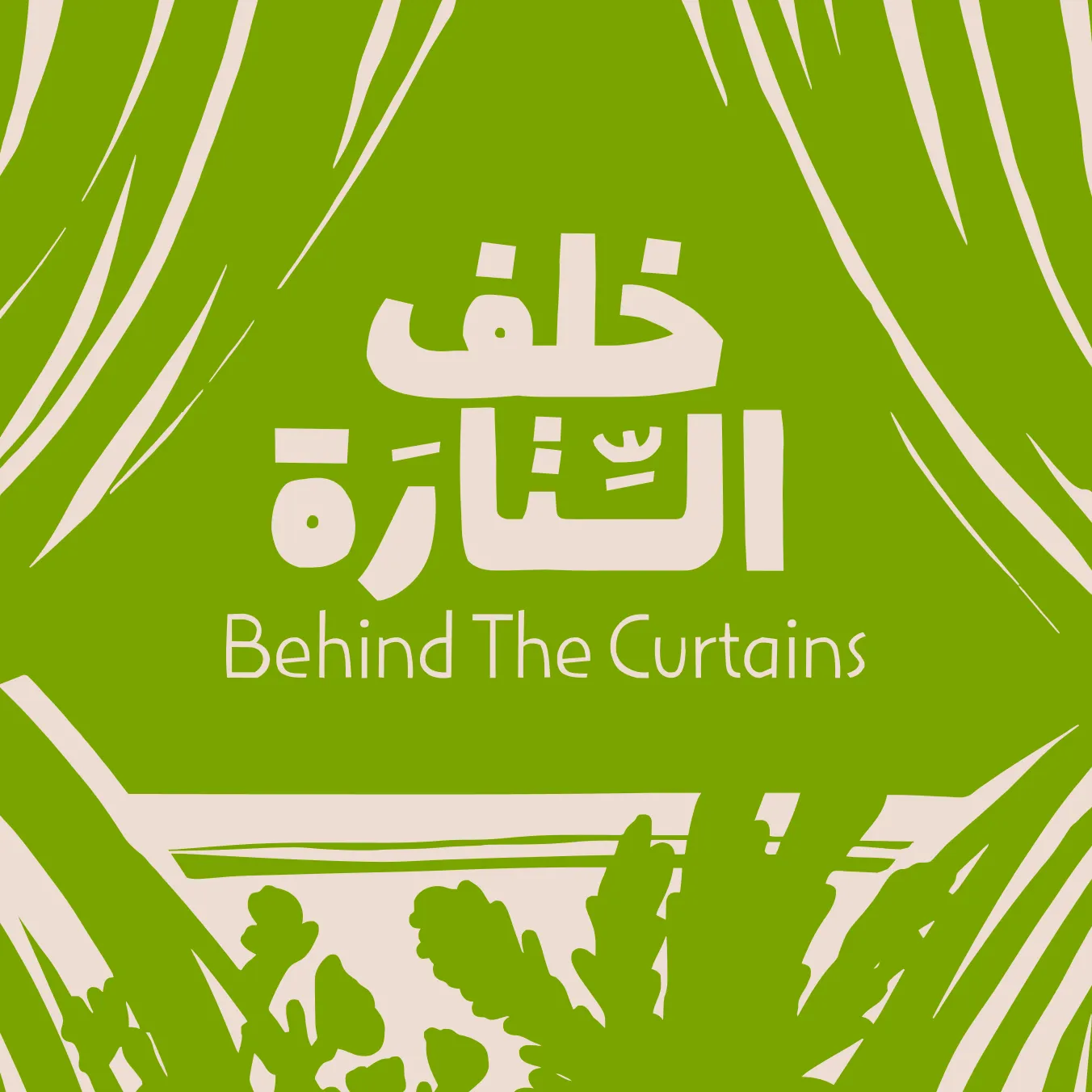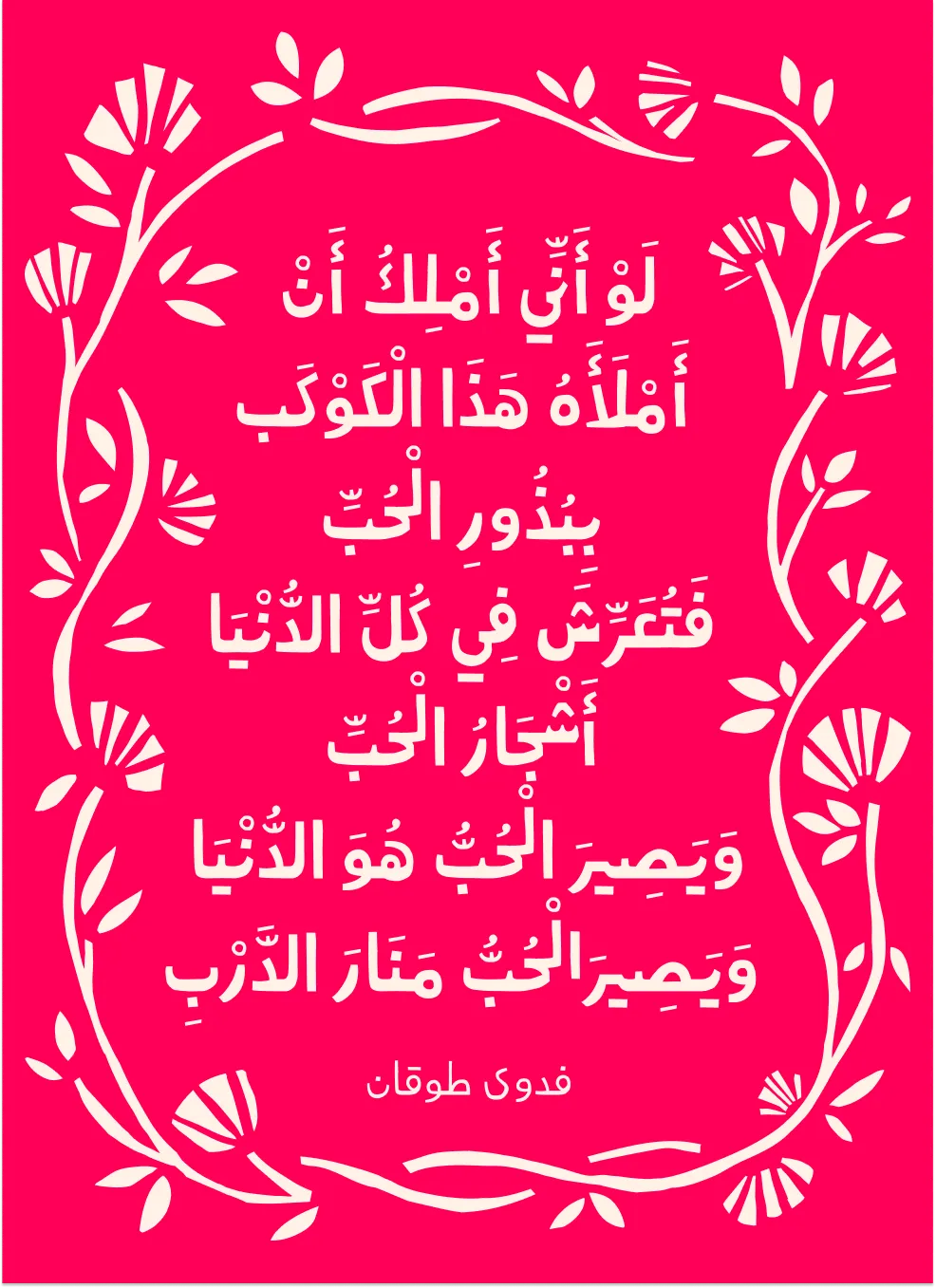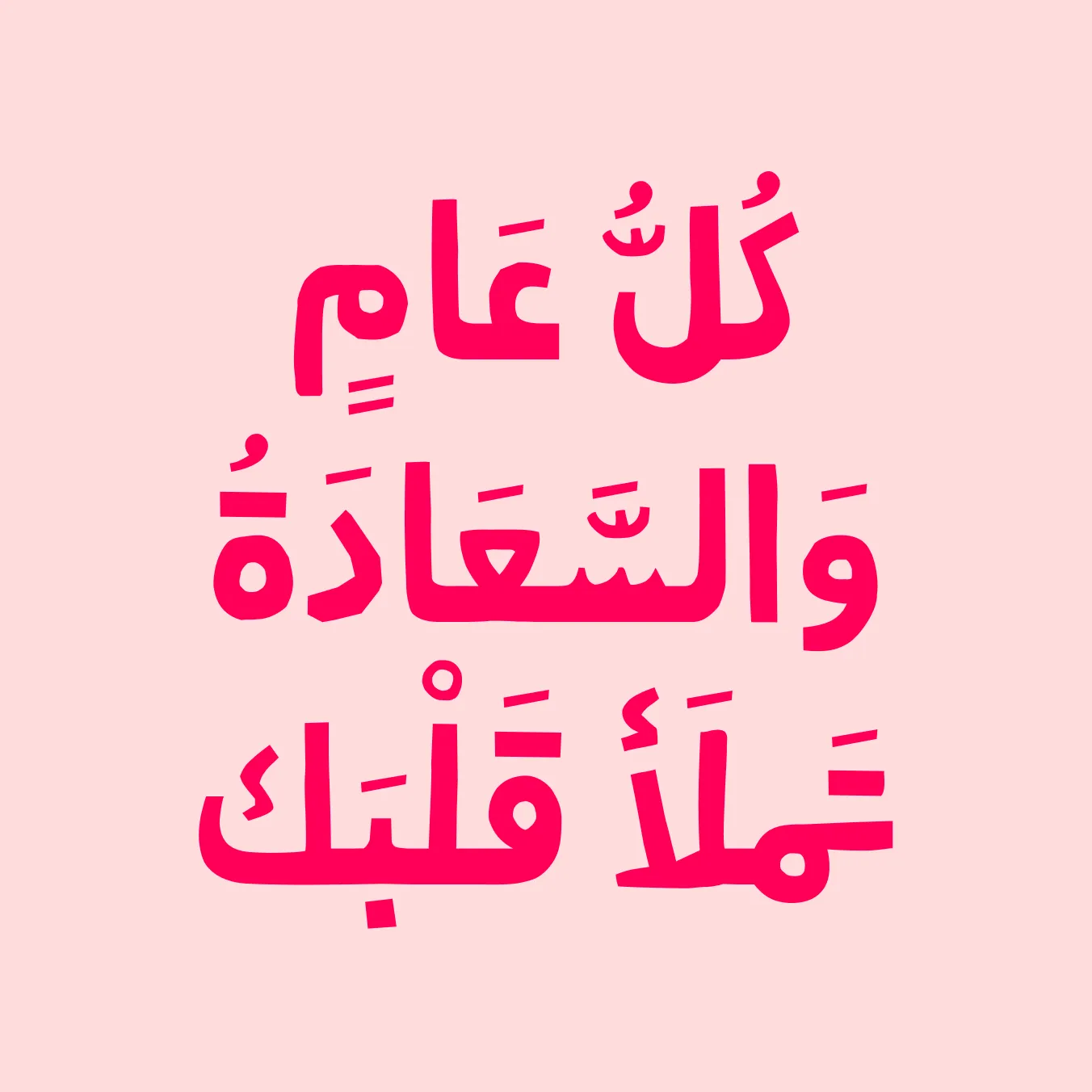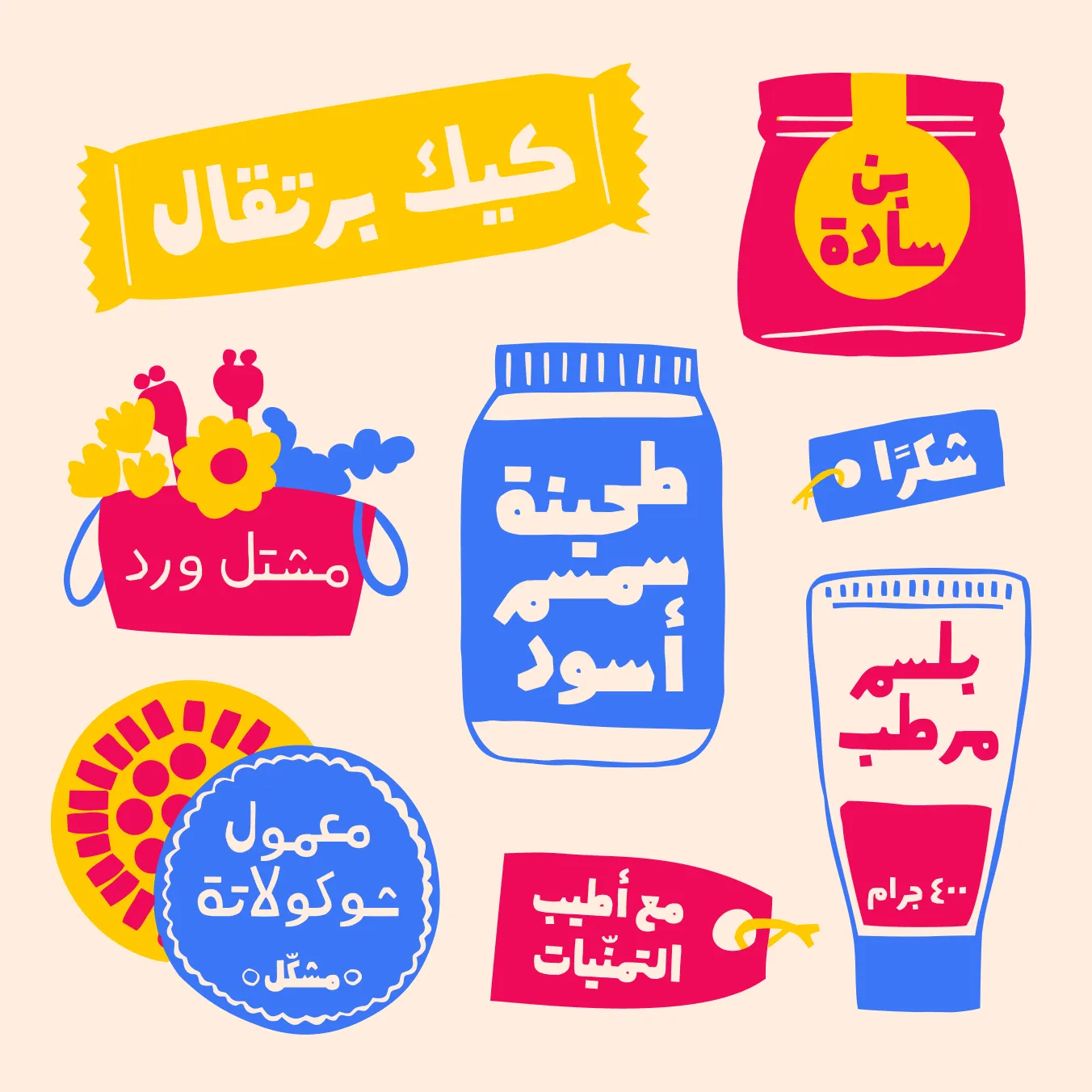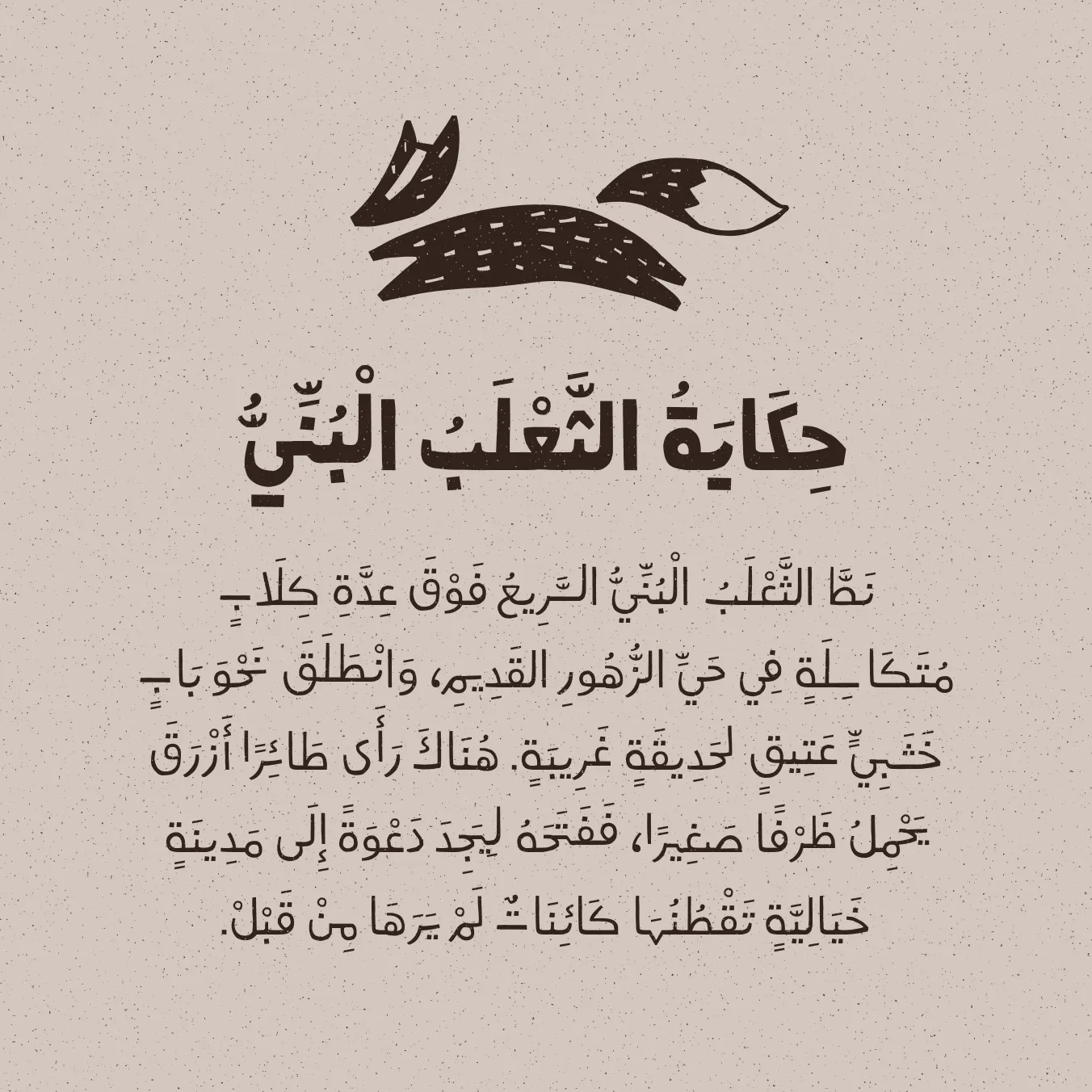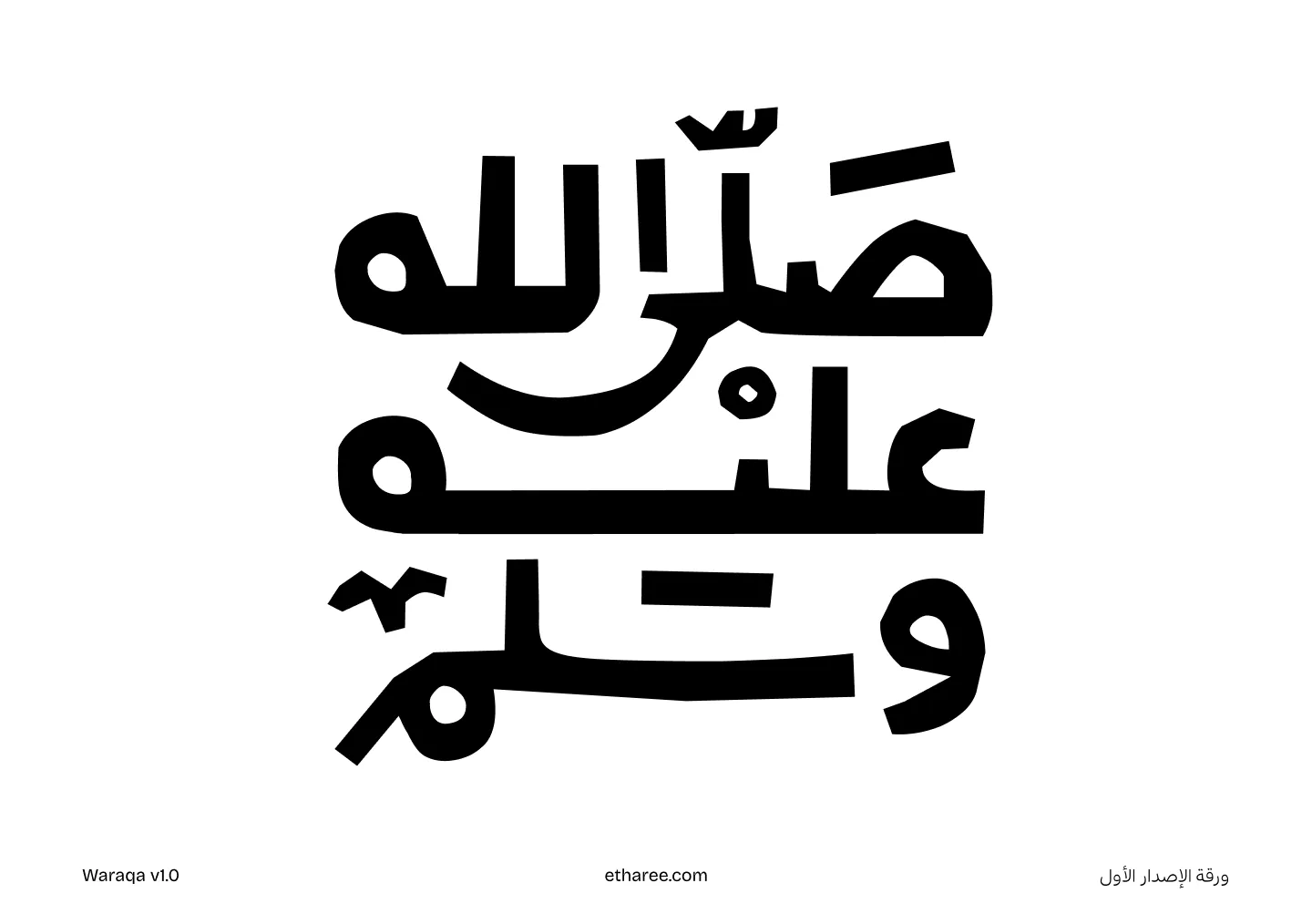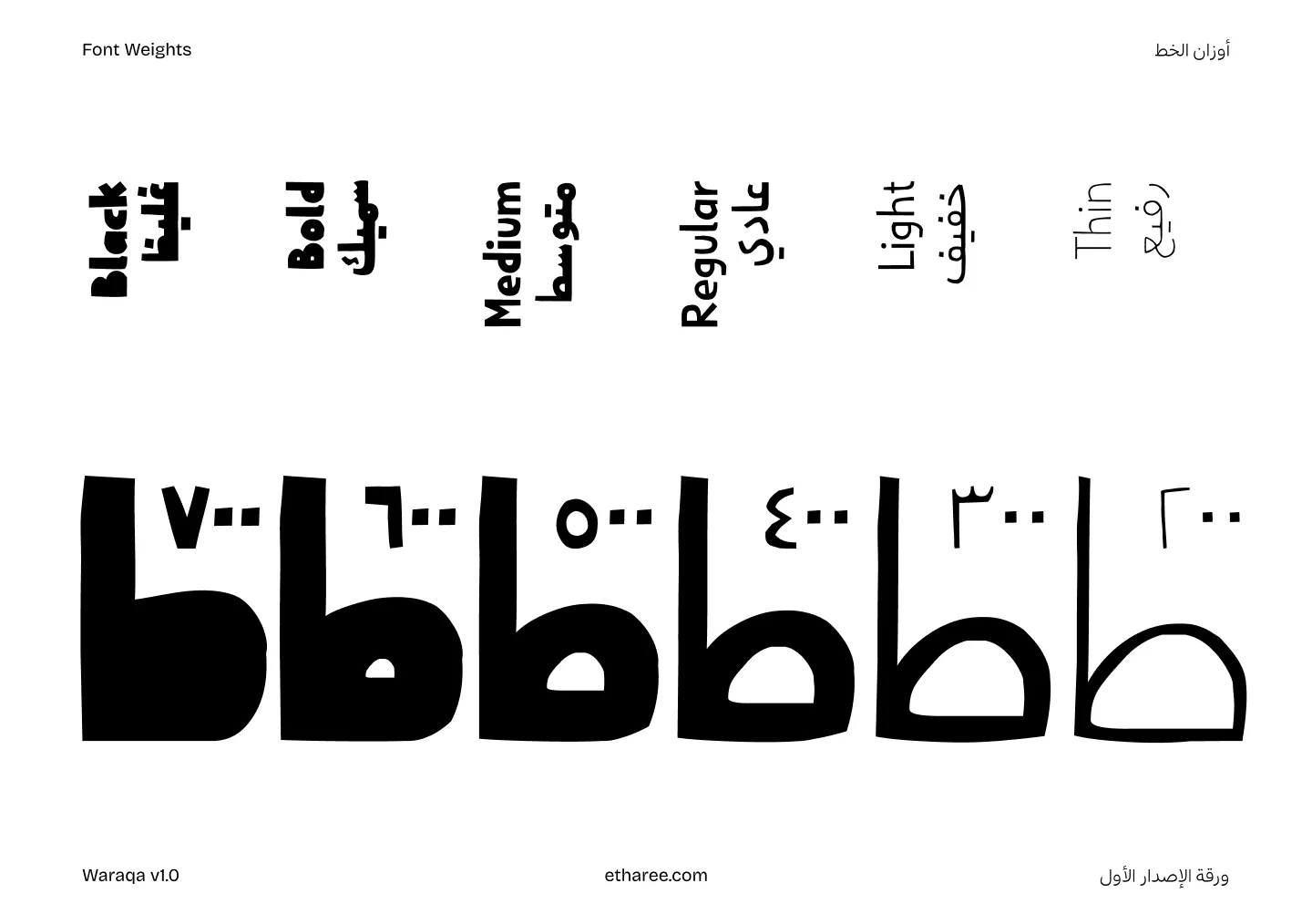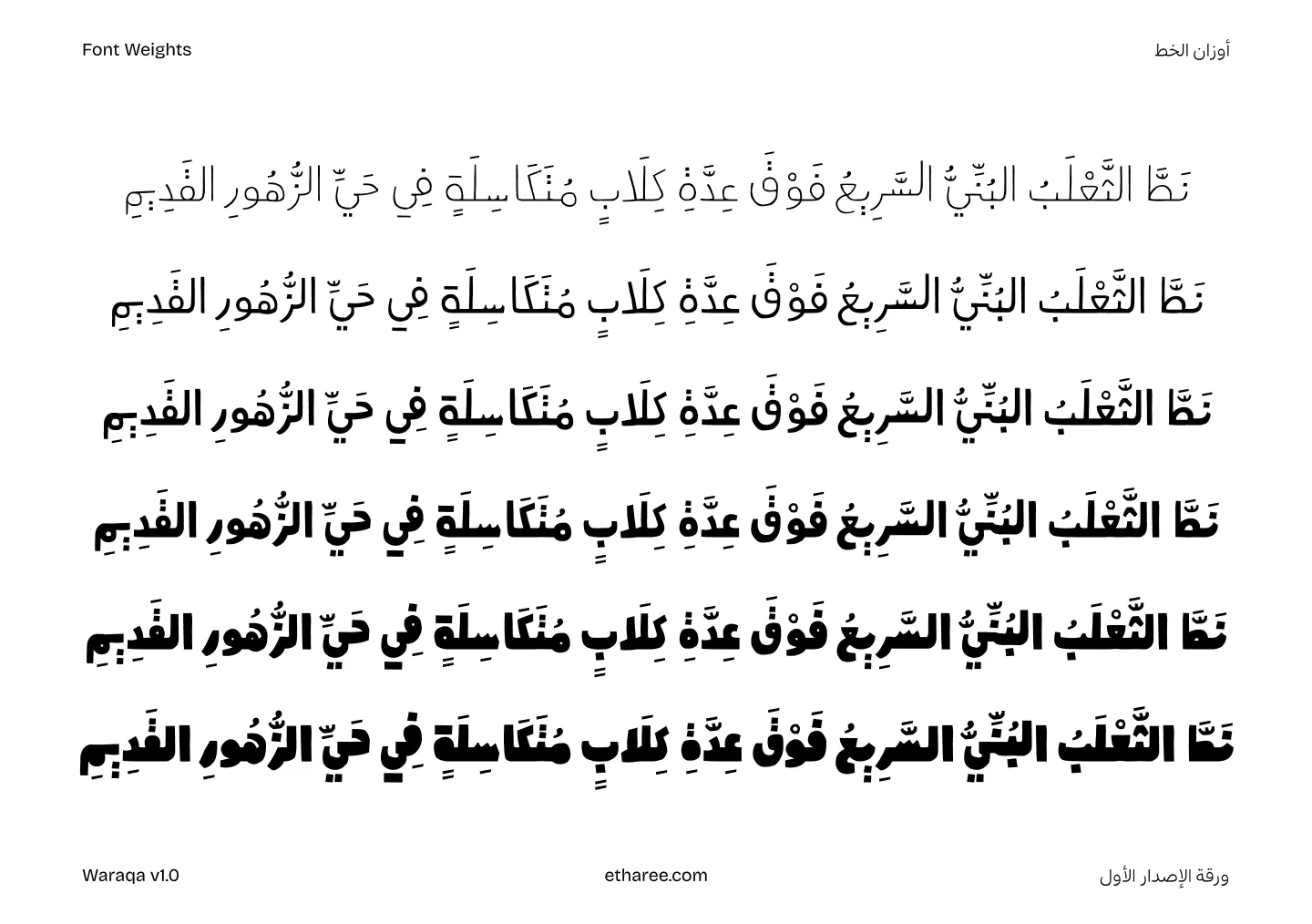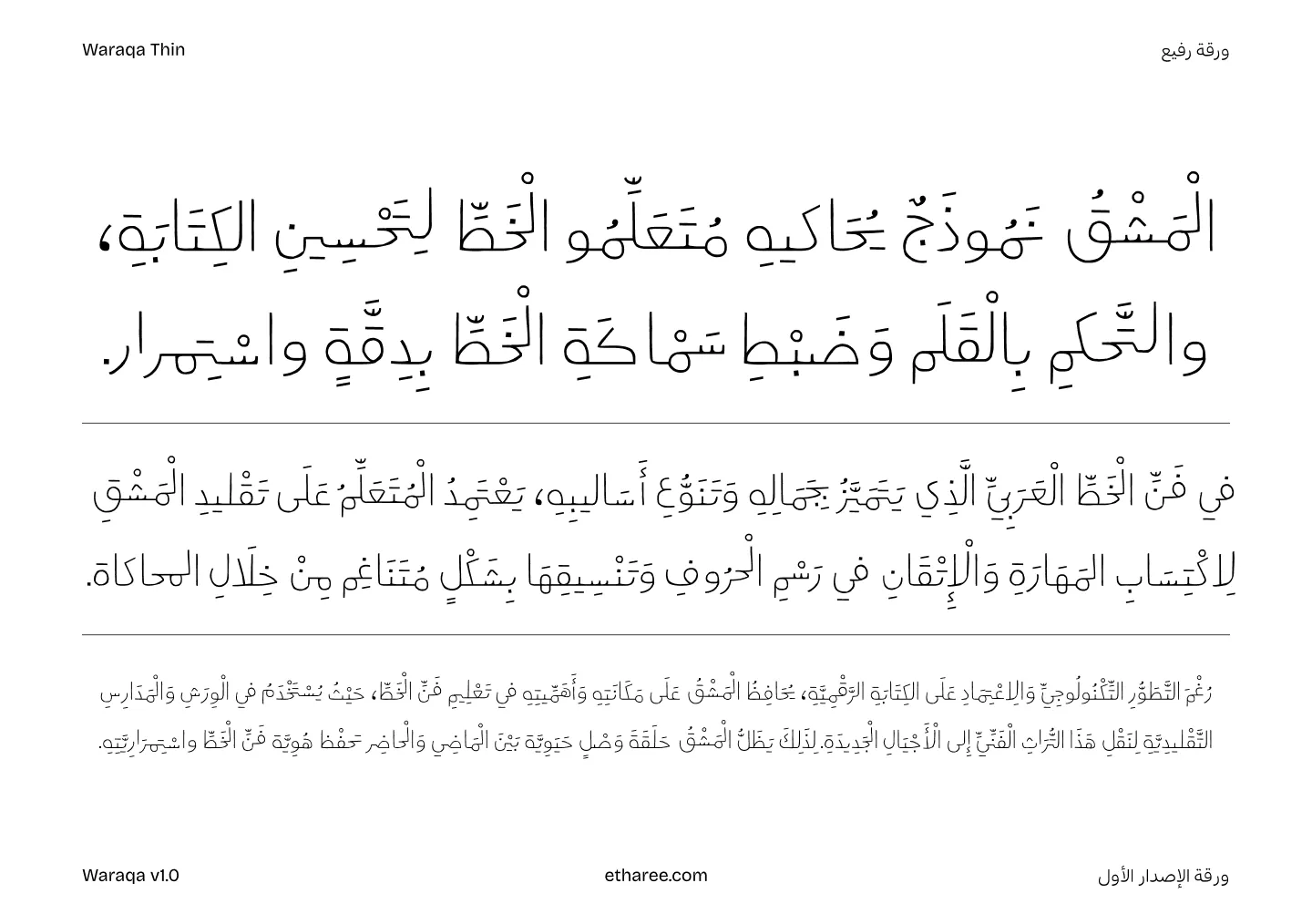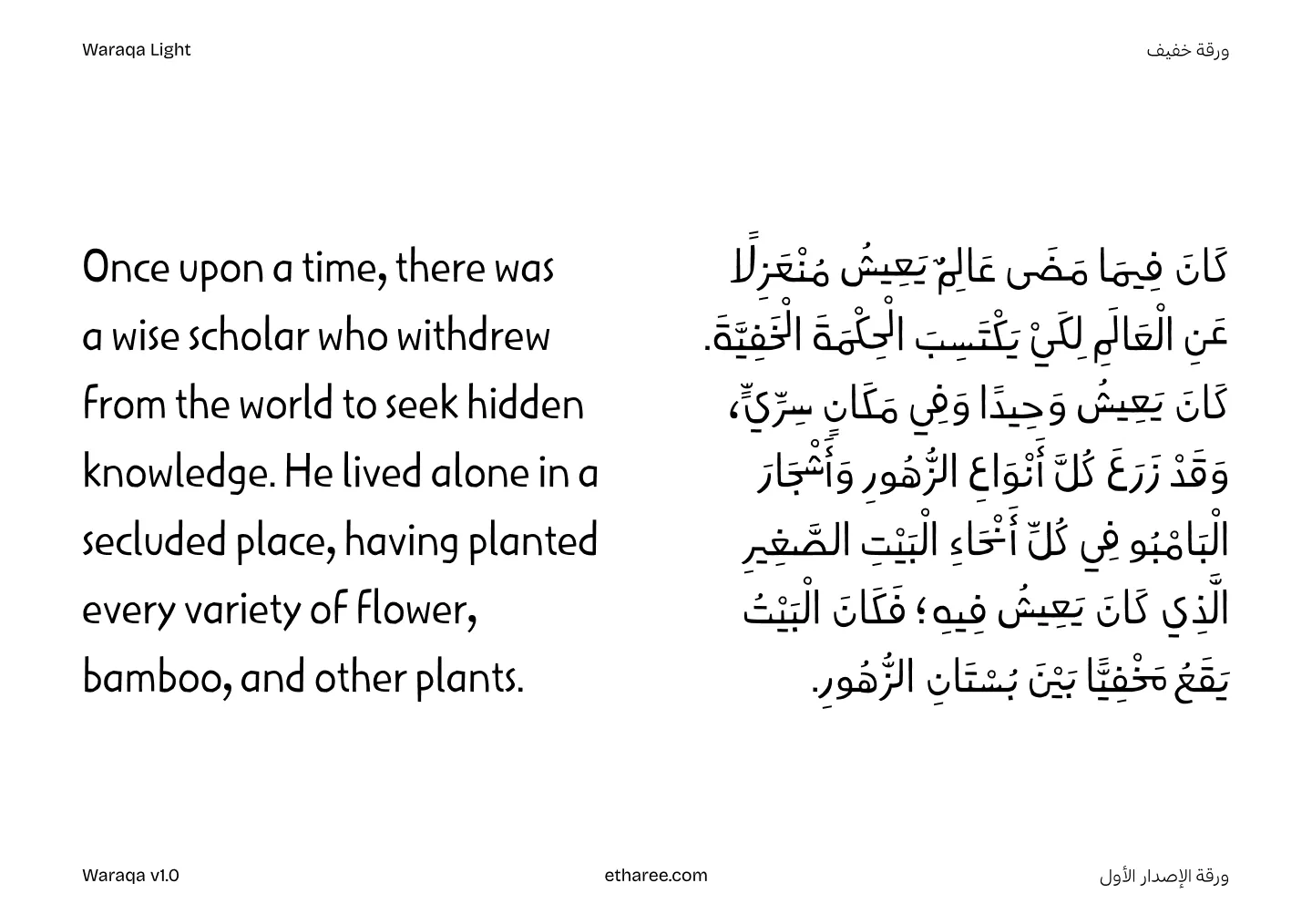
ss01
نقطتان أفقيتان
ss02
نقطتان رأسيتان
ss03
ثلاث نقاط منفصلة
ss04
باء بديلة
ss05
سين بديلة
ss06
عين وسطية بديلة
ss07
فاء بديلة
ss08
كاف زنادية
ss09
كاف بديلة
ss10
ميم بديلة
ss11
هاء بديلة
ss12
لام ألف بديلة
ورقة خط عربي متغير يجمع بين الأشكال الهندسية  والطابع اليدوي مع تفاصيل مستوحاة من القص الورقي. تتدرّج أوزان الخط من الرفيع إلى الأسود الكثيف، حيث تتقلص فراغات الأشكال تدريجيًّا حتى تُطمس. صُمم الخط للعناوين، وأغلفة الكتب، والهويات البصرية.